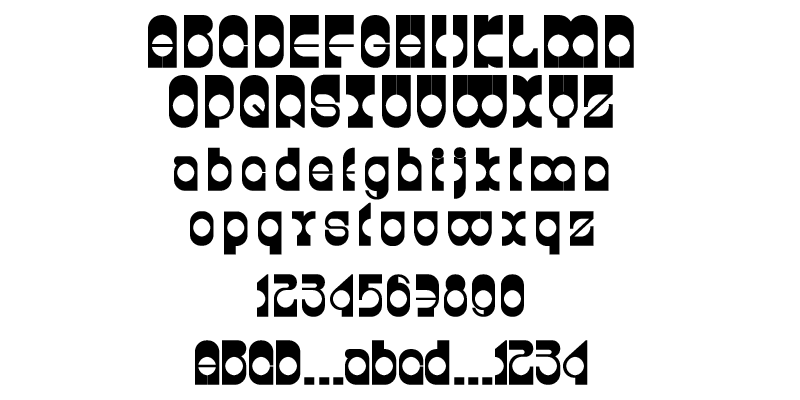
Tipografía gratuita: la tipografía de este mes llega desde 1972 pero es totalmente actual.
La tipografía gratuita Lucky fue diseñada por André Pless (Mecanorma) en 1972 y digitalizada y cedida a Neo2 por Andrea Bianchini en 2019.
Es una tipografía de estilo decorativo o display. La tipo utiliza formas redondas muy prominentes en sus contraformas. Las letras son alargadas y tienen un grosor muy elevado. La tipografía Lucky juega mucho con los contrastes entre líneas finas y formas corpulentas, y entre ángulos puntiagudos y círculos perfectos.
La tipografía gratuita Lucky tiene una extravagancia conquistadora. Además, su esencia es muy retro, recordándonos al mismo tiempo al Oeste americano y al estilo de los años 70. Es perfecta para crear títulos súper expresivos de una determinada estética.
La tipo Lucky, creada en 1972, tiene versión en caja alta, en caja baja y con números.
Free typeface: this month’s typeface “Lucky” is from 1972 but it’s completely relevant today.
This free typeface called Lucky was designed by André Press (Mecanorma) in 1972 and digitized and granted to Neo2 by Andrea Bianchini in 2019.
It’s a typeface with decorative style or so-called display. Lucky uses very prominent round shapes as negative space and the letters are long and condensed, having really thick strokes. The typeface plays with the contrast between thin lines and bulky shapes, and between spiky angles and perfect circles.
The typeface has a conquering flamboyance. Also, its’ essence is quite retro, taking us back either to the American Wild West or to the style of the 70s. It’s perfect for designing super expressive titles with a very particular aesthetic.
The free Lucky typeface, created in 1972, has an upper case, a lower case and a numbered version.